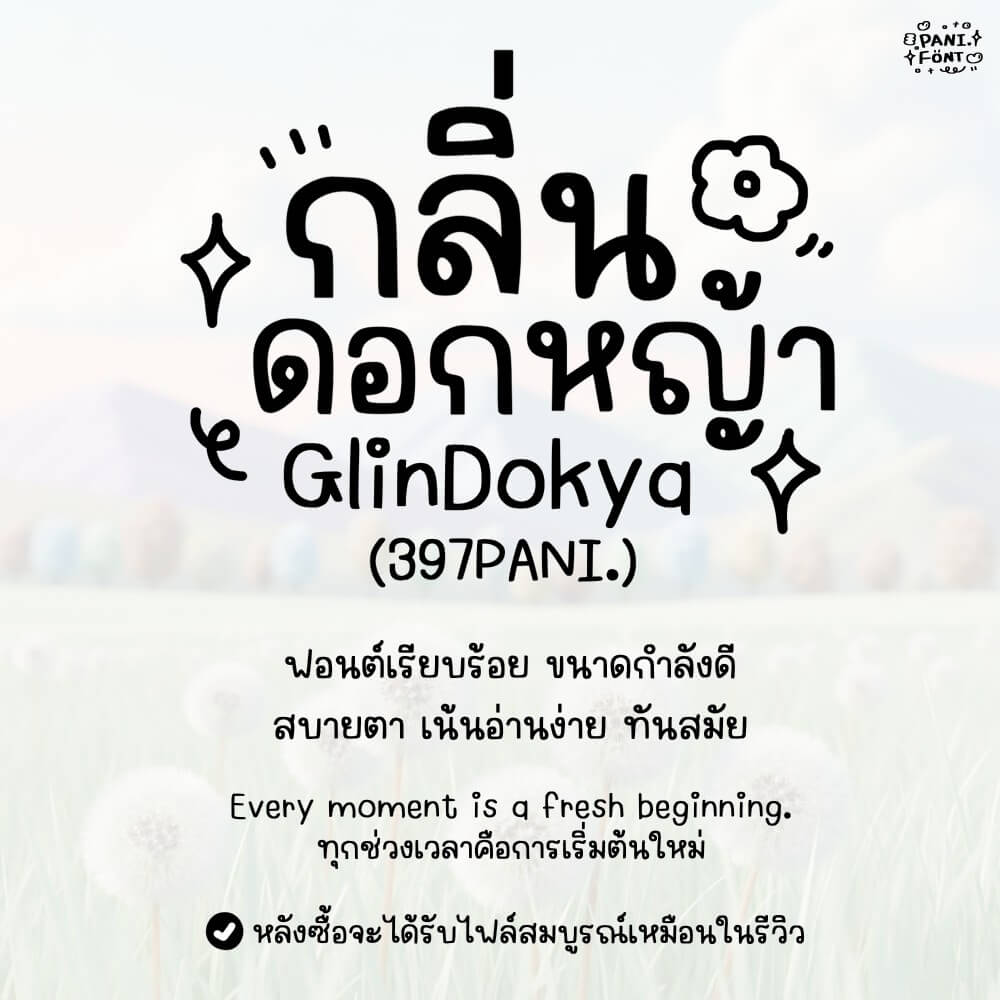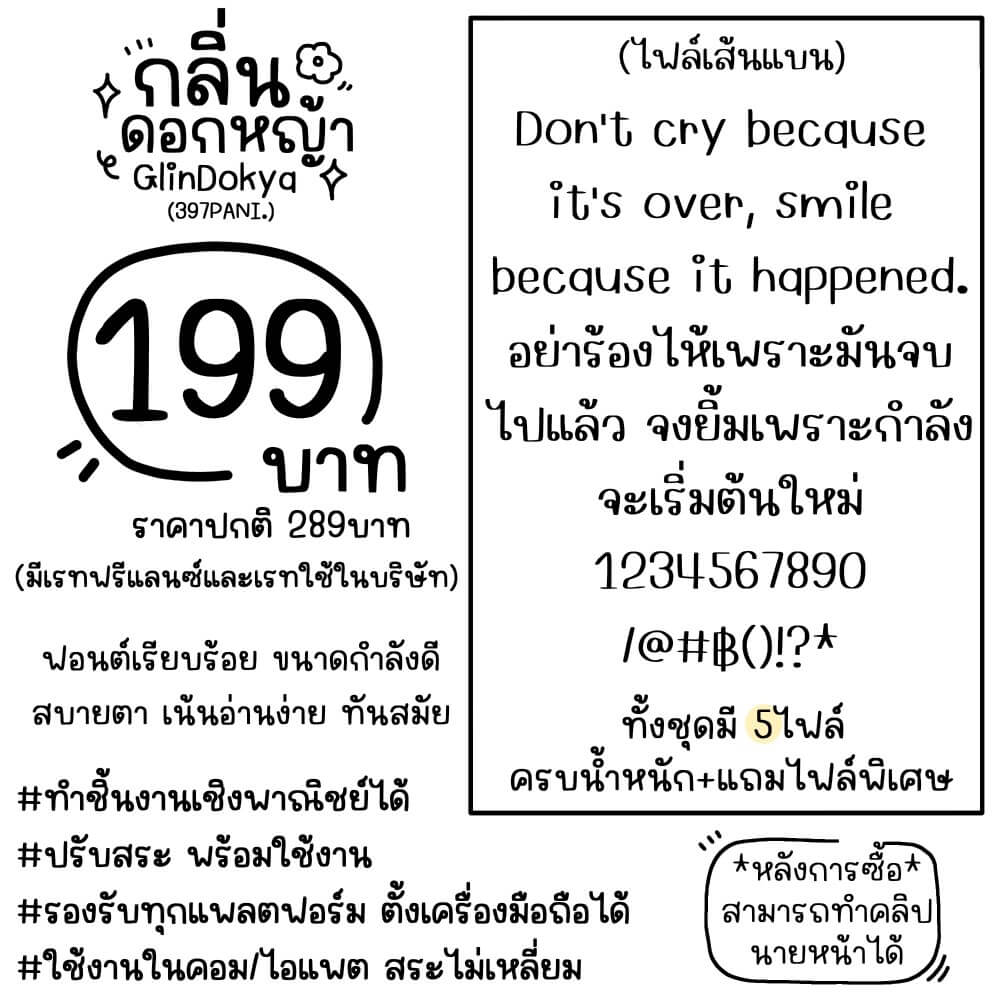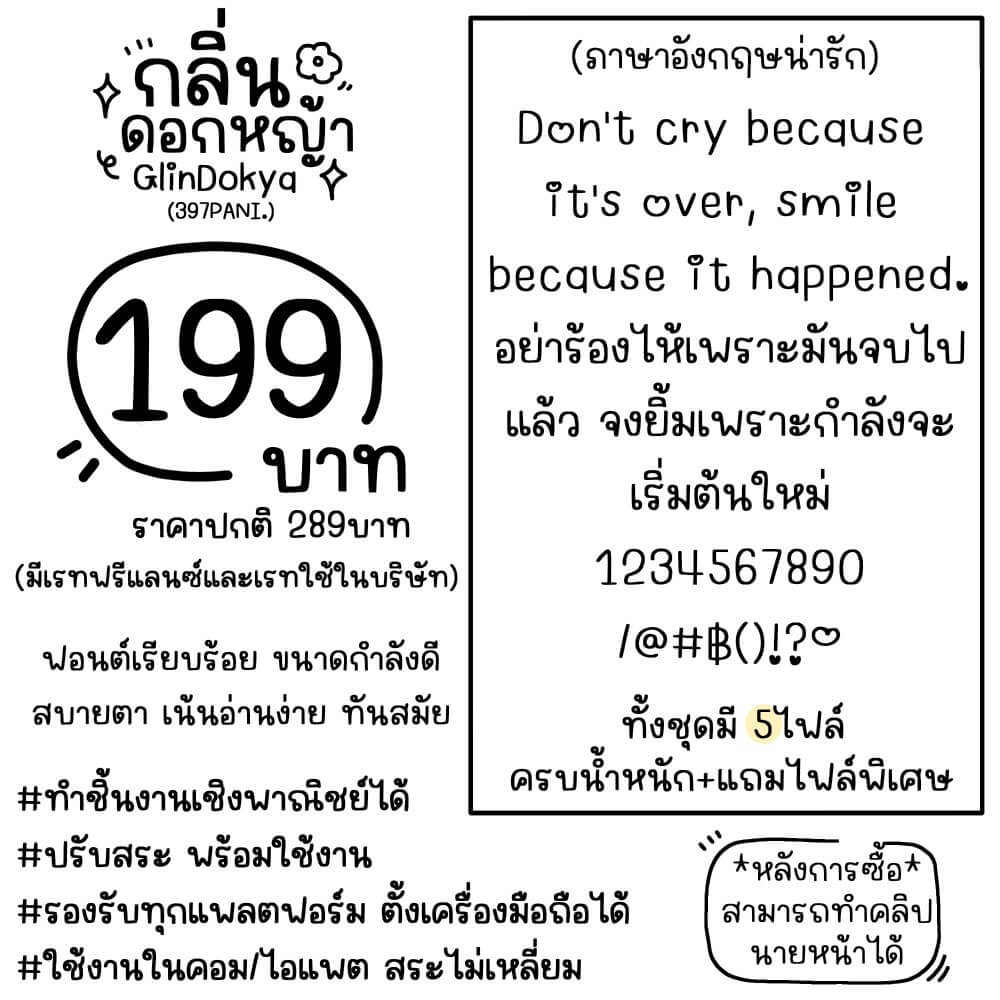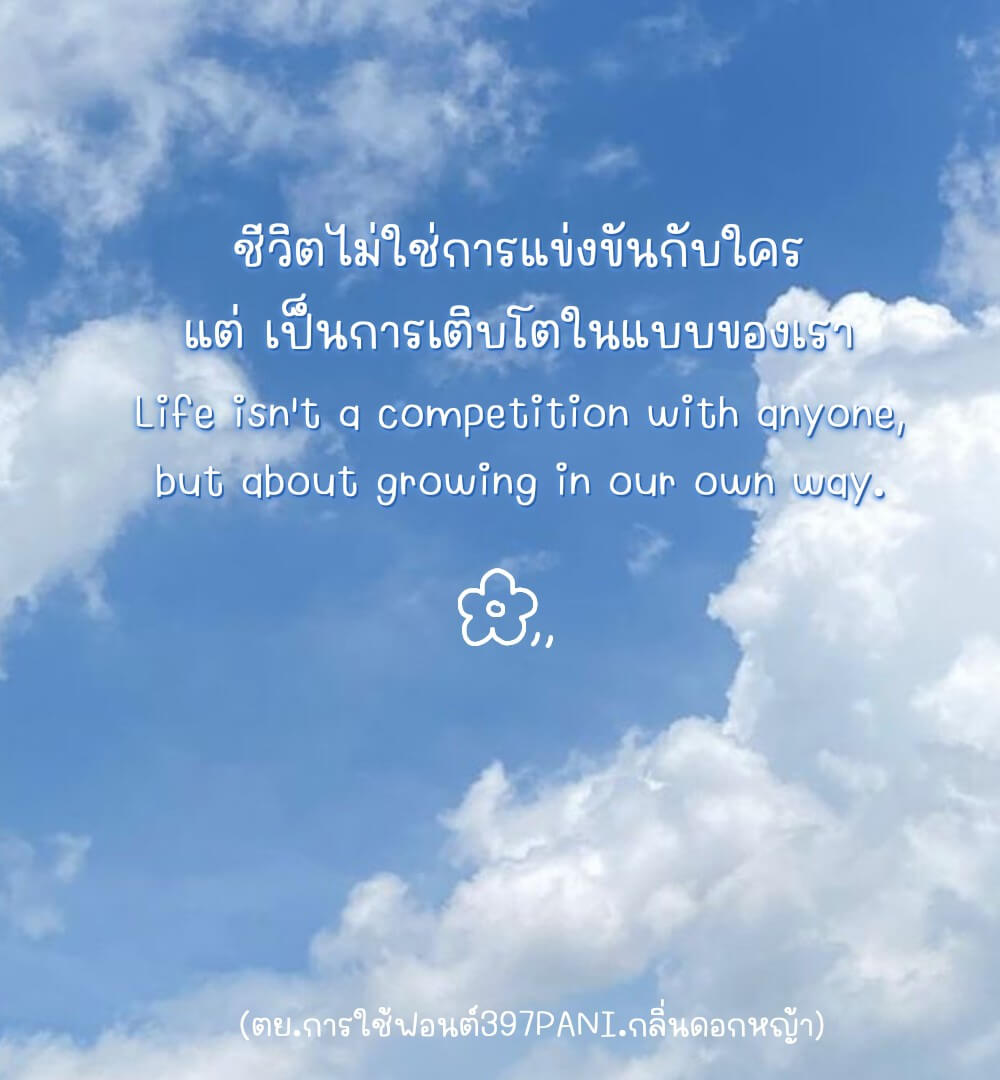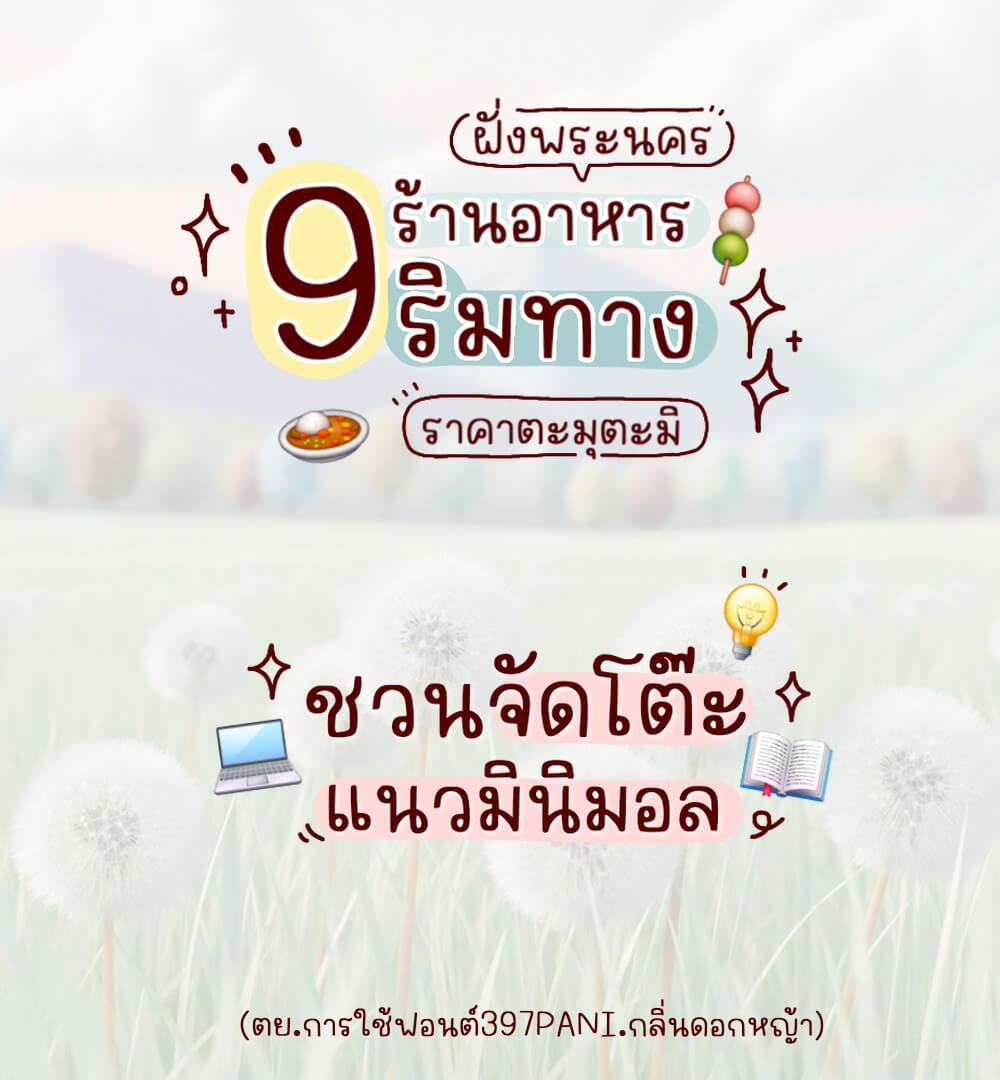
397PANI.กลิ่นดอกหญ้า
ฟอนต์ 397PANI.กลิ่นดอกหญ้า – ฟอนต์แนวละมุนตา เรียบร้อย อ่านง่าย ขนาดตัวกำลังพอดี ใช้งานได้หลากหลาย ไฟล์เส้นแบนกึ่งทางการ และใครชอบความน่ารัก ต้องชอบไฟล์ Cute